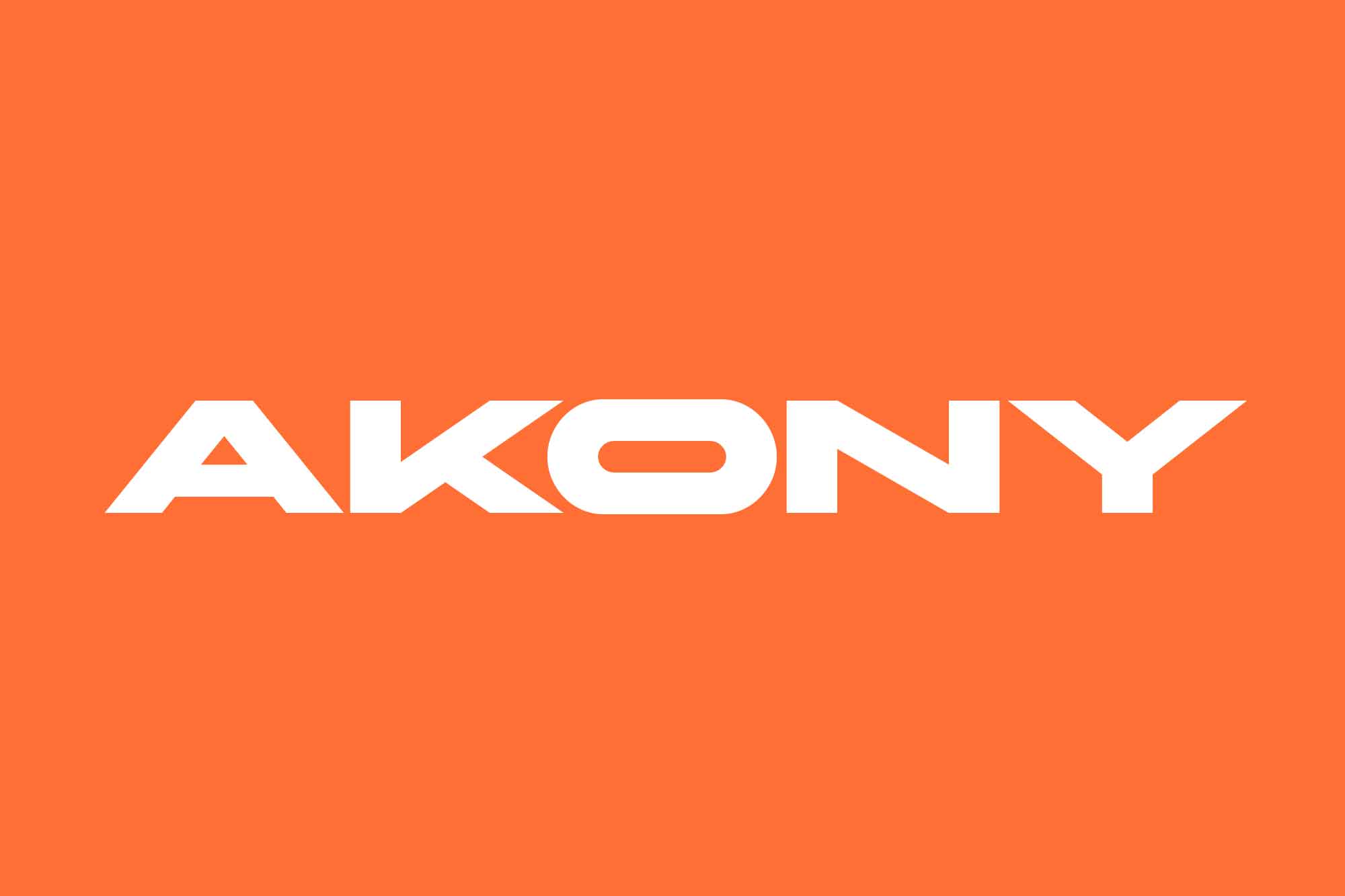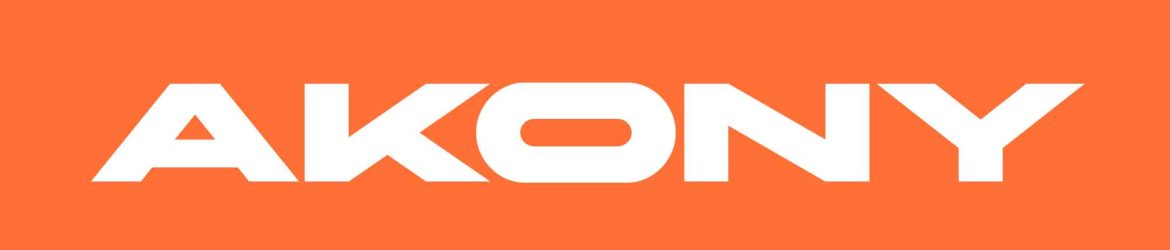
A Akony Display Font é um tipo de letra capitalizada semicompacta desenvolvida para uso em aplicativos de alta projeção. Seu corpo robusto é perfeito para titulos, cartazes, marcações e embalagens. Esta tipografia é uma verdadeira atracção, tornando seu trabalho mais chamativo e aumentando sua audiência. Foi cuidadosamente criada com atenção aos parágrafos de espaço, dimensões das letras e outros aspectos que contribuem para uma fonte agradável aos olhos. Englobando tanto a elegância quanto a robustez, a Akony Display Font é uma escolha ideal para criar impacto no seu próximo projeto visual.